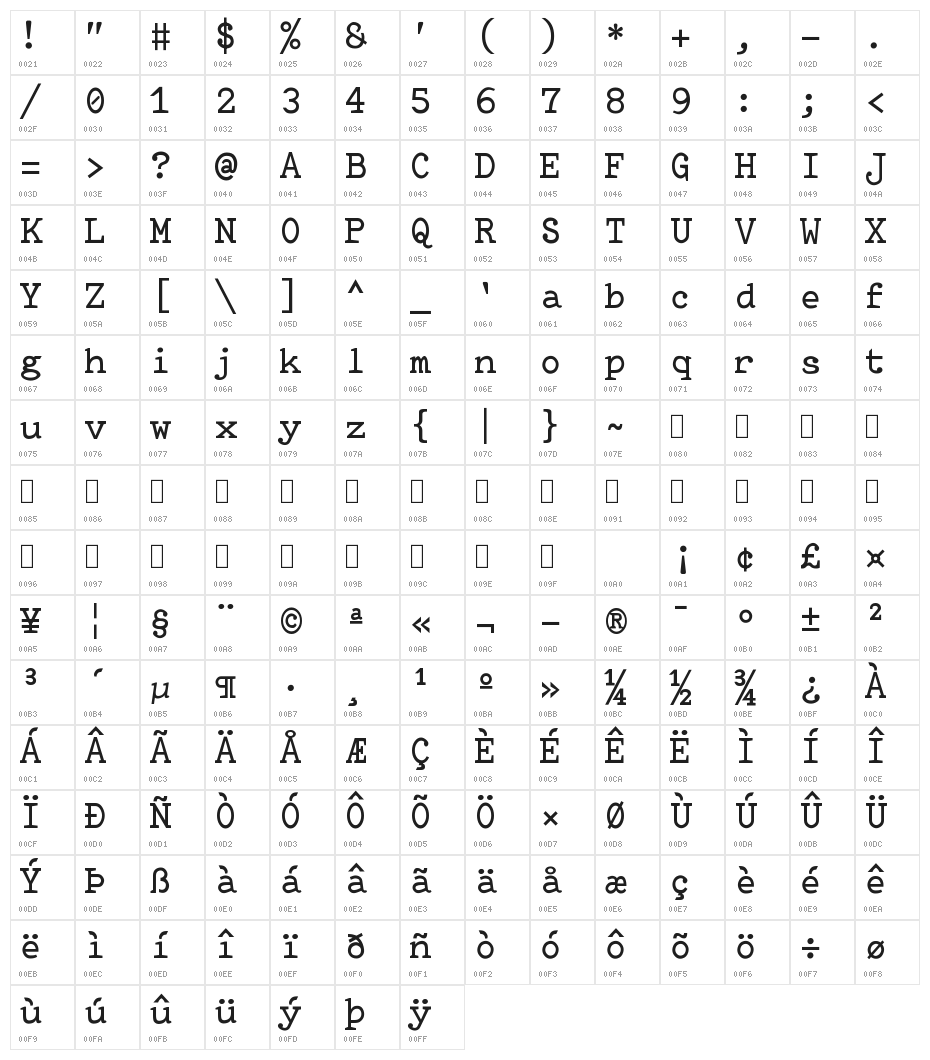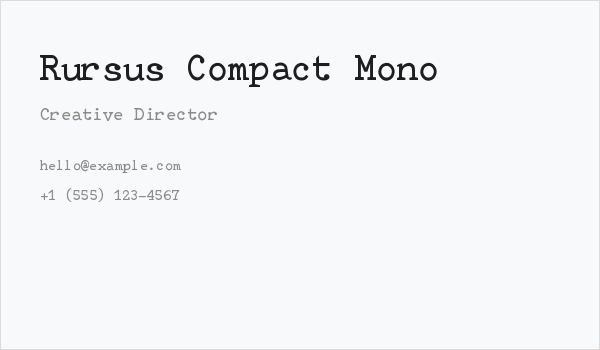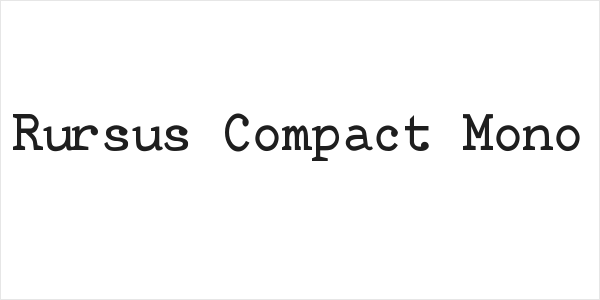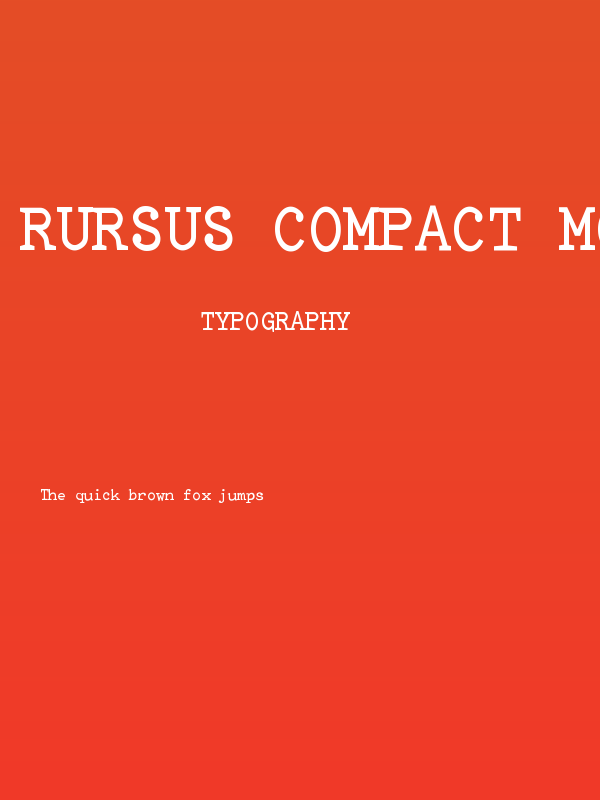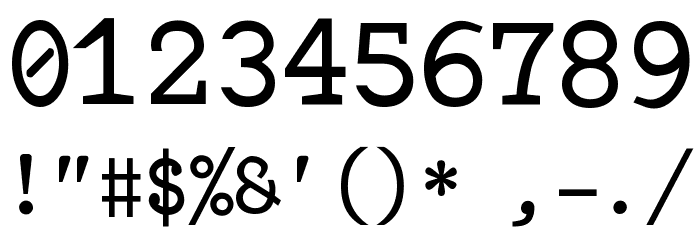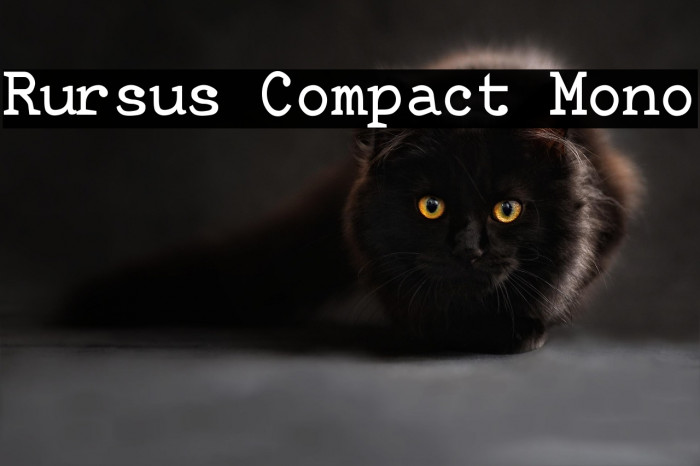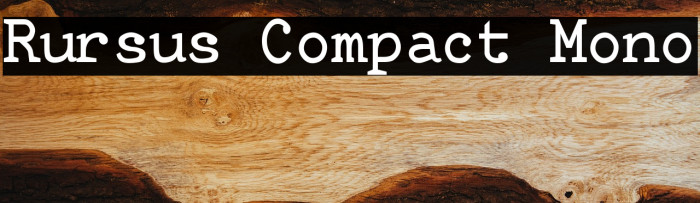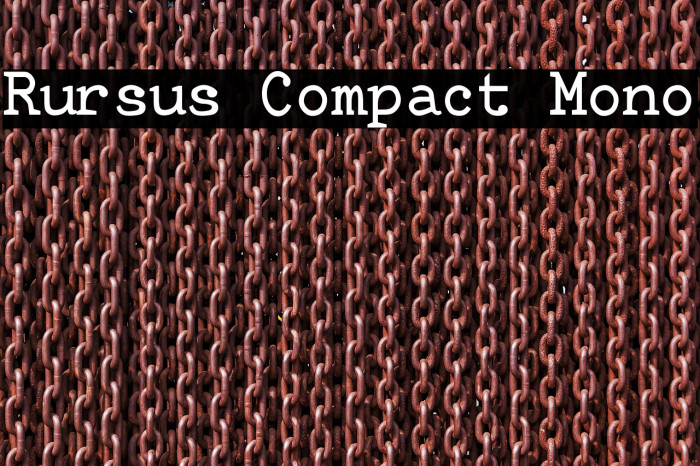
Rursus Compact Mono Font
✎ Typewriter
| Categorías | Typewriter |
| Estilo general | Classic |
| Caso de uso | Technical documents, Coding, Print media |
| Proyectos propuestos | Ideal for coding, technical documents, and any project requiring a monospaced font for clarity and precision. |